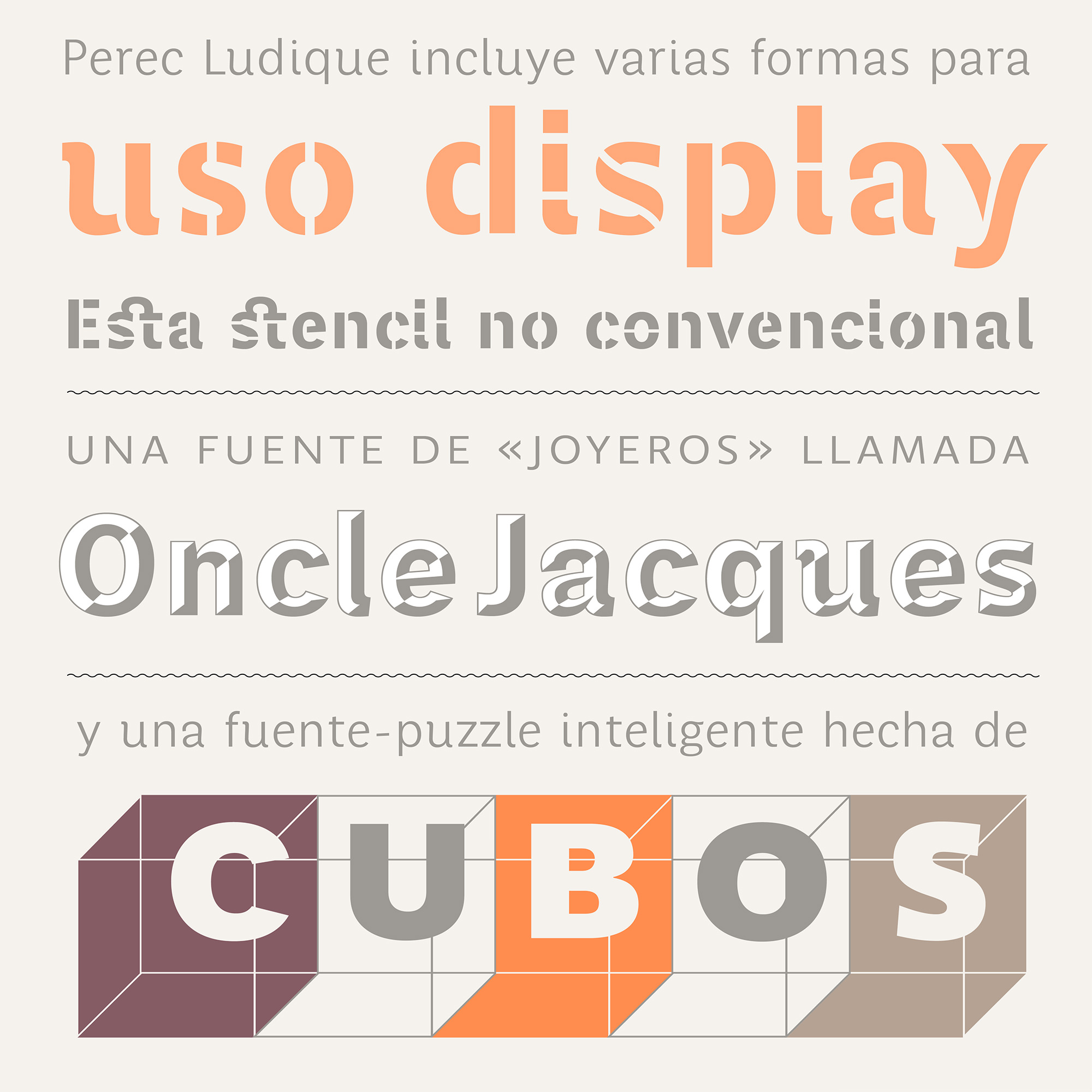
Perec Ludique 2.0
Perec Ludique, que forma parte de la familia Perec, ha sido actualizada seriamente y ahora incluye amplia cobertura idiomática además de nuevas características OpenType. Pruébala.